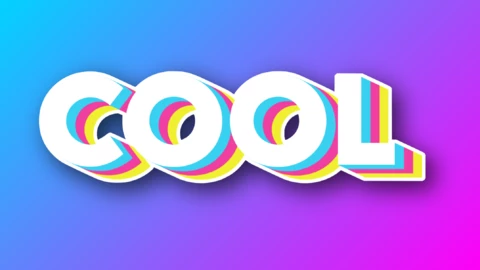
Texte 3D bleu jaune rose
Alice In Wonderland Font Effet de Texte
Créez un effet de texte "Alice In Wonderland Font" 3d bleu jaune rose grâce à notre générateur de polices personnalisées en ligne.